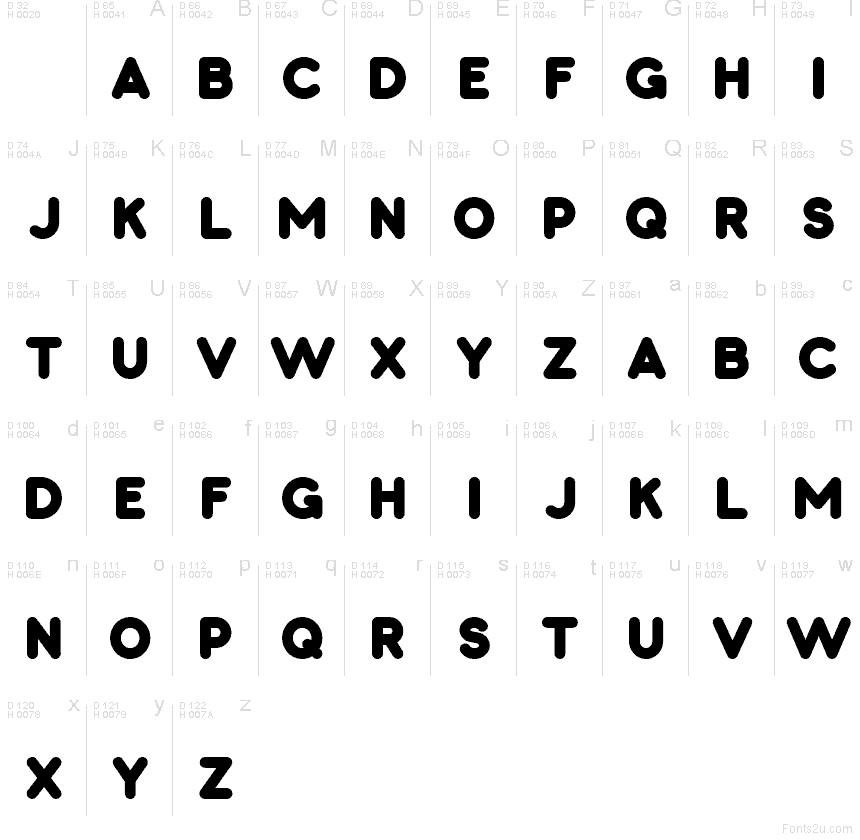
GODAM
Setyaisiamによる「Godam」は、丸みを帯びた幾何学的なサンセリフ体で、重厚感のある無料フォントです。大文字は柔らかさと安定感を兼ね備えており、ゆったりとした曲線、スクエアなプロポーション、そして均一なリズムが、厳格なモダニズムとは一線を画す、親しみやすくポスターのような雰囲気を演出します。
ブランディング、音楽イベントのフライヤー、パッケージ、SNSの投稿、そして強いインパクトが必要なタイトルデザインに最適です。無料で使えるGodamは、カバーデザインやモノグラム、大胆なラベル作りにも役立ちます。太めのシェイプと丸みを帯びた角により、大きな文字設定でも親しみやすい印象を与えます。